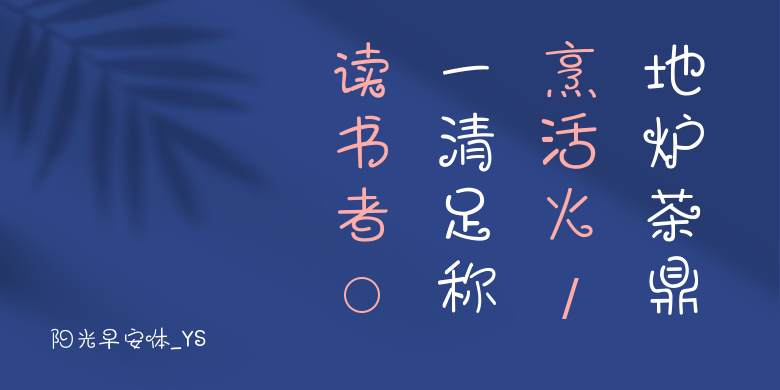
阳光早安体_YS
阳光早安体_YS,这款字体结构工整、笔画清晰,兼顾美观与易读性,适用于标题、正文、海报、包装、LOGO 等多种场景。字形优雅稳定,风格百搭耐看,适配日常排版与创意设计,让文字呈现更舒适、更具质感。阳光早安体_YS一笔一画,皆是细节,以均衡的比例、流畅的线条打造舒适视觉体验,字形端正大气,风格简约现代。无论是商业设计、品牌宣传还是日常排版,都能轻松驾驭,让文字更有格调与力量。阳光早安体_YS字体下载。